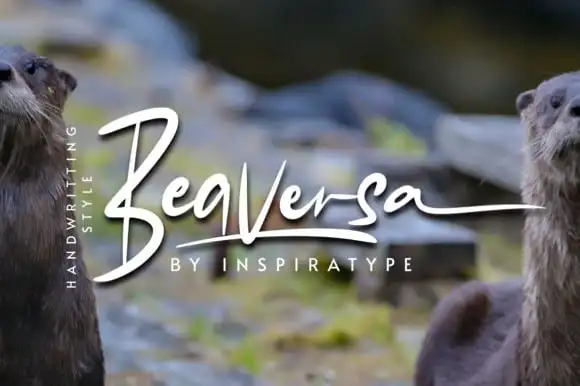
Beaversa Script Font – Fonte Grátis
Beaversa Script Font
Beaversa Script Font é uma fonte casual com toque de letra à mão que oferece um encanto elegante para seus projetos digitais. Ela se destaca na categoria de tipos de script, combinando a natureza fluida dos caracteres escritos à mão com o estilo do desenho manual, criando um efeito único de personalização. Inspiratype Studio é o designer responsável por este projeto que vem acompanhado das letras maiúsculas e minúsculas, números e pontuação. Além disso, ela inclui uma variedade de alterações em OpenType, ligaturas comuns e até mesmo swashes para você personalizar suas criações conforme necessário. Perfeita para uso em logotipos, cartões de carta, posters, desenho de roupas, etiquetas e muito mais. Beaversa Script Font é uma opção ideal para quem busca uma fonte que oferece tanto estilo quanto flexibilidade para personalização.